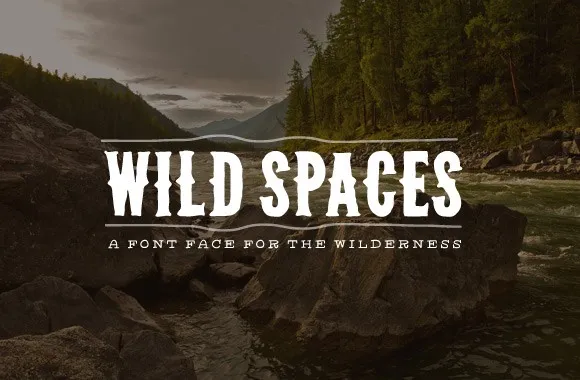
Wild Spaces Typeface – Fonte Grátis
Wild Spaces Typeface
Introduzimos a Wild Spaces Typeface! Esta fonte foi criada e compartilhada pela WeGraphics e é perfeitamente adaptada para quem vive entre as encantadoras paisagens do interior, sejam eles nas montanhas onde a brisa sopra fresca e nos bosques que abrigam vida selvagem. Wild Spaces está em perfeita harmonia com qualquer aventura de natureza, seja você deslizando pela estrada de pedras ou sentado confortavelmente na grama do seu acampamento. Perfeito para sua próxima jornada nas encostas do caminho menos trilhado ou pelo topo da montanha mais alta. A Wild Spaces Typeface é a escolha perfeita para quando você quer expressar um espírito de aventura e conexão com o espaço ao ar livre em seu próximo projeto visual.